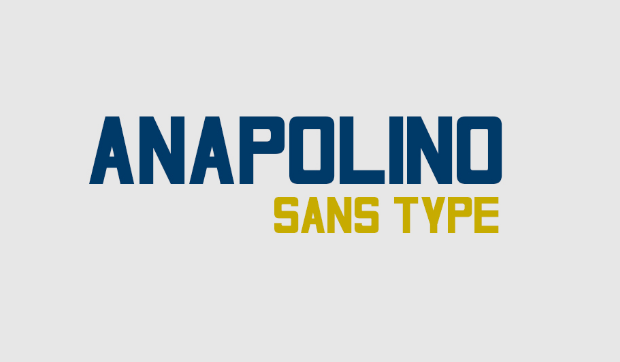
ANAPOLINO é uma fonte sem serif livre projetada pelo designer Hamilton. Ela traz uma atmosfera clássica, mas com uma delicadeza que a torna única e encantadora. Este projeto de geração digital, disponibilizado por Gleydson Isecke, oferece uma experiência visual singular que você encontrará ao baixar ANAPOLINO. A sua beleza transborda em cada letra, combinando elegância com versatilidade, tornando-se um recurso indispensável para qualquer designer gráfico ou criador de materiais digitais. Seja para aplicativos web, projetos impressos ou designs digitais interativos, ANAPOLINO oferece aprimoramentos que o vão surpreender e transformarão seus trabalhos em verdadeiros clássicos do design. Instale-a agora e descubra novas possibilidades no seu trabalho.